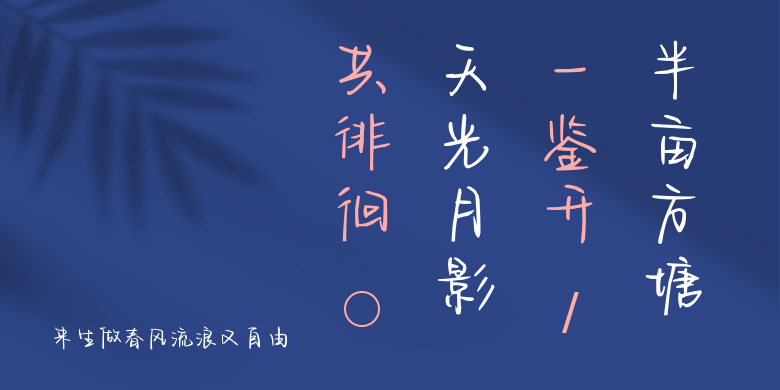
来生做春风流浪又自由
来生做春风流浪又自由,这款字体结构工整、笔画清晰,兼顾美观与易读性,适用于标题、正文、海报、包装、LOGO 等多种场景。字形优雅稳定,风格百搭耐看,适配日常排版与创意设计,让文字呈现更舒适、更具质感。来生做春风流浪又自由一笔一画,皆是细节,以均衡的比例、流畅的线条打造舒适视觉体验,字形端正大气,风格简约现代。无论是商业设计、品牌宣传还是日常排版,都能轻松驾驭,让文字更有格调与力量。来生做春风流浪又自由字体下载。